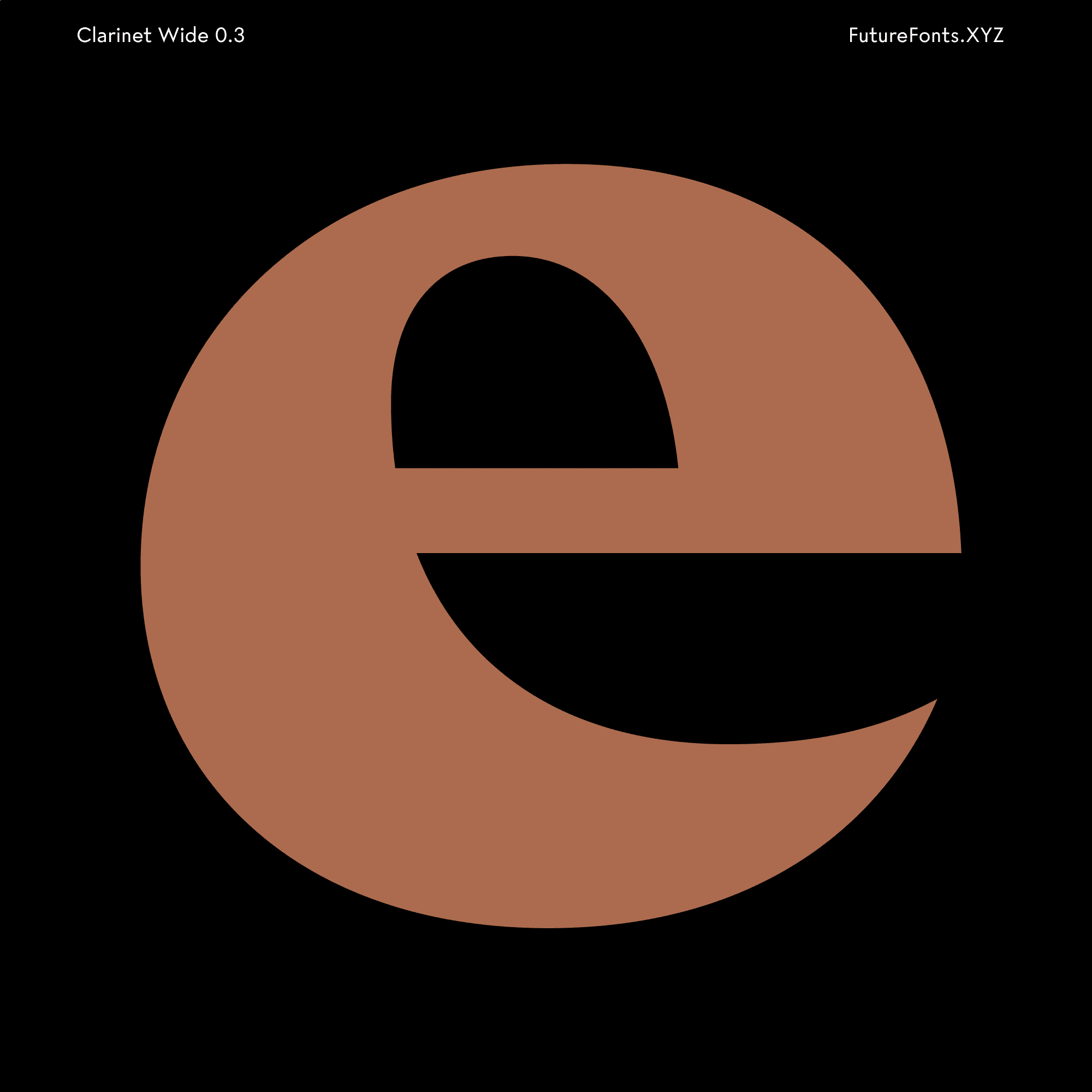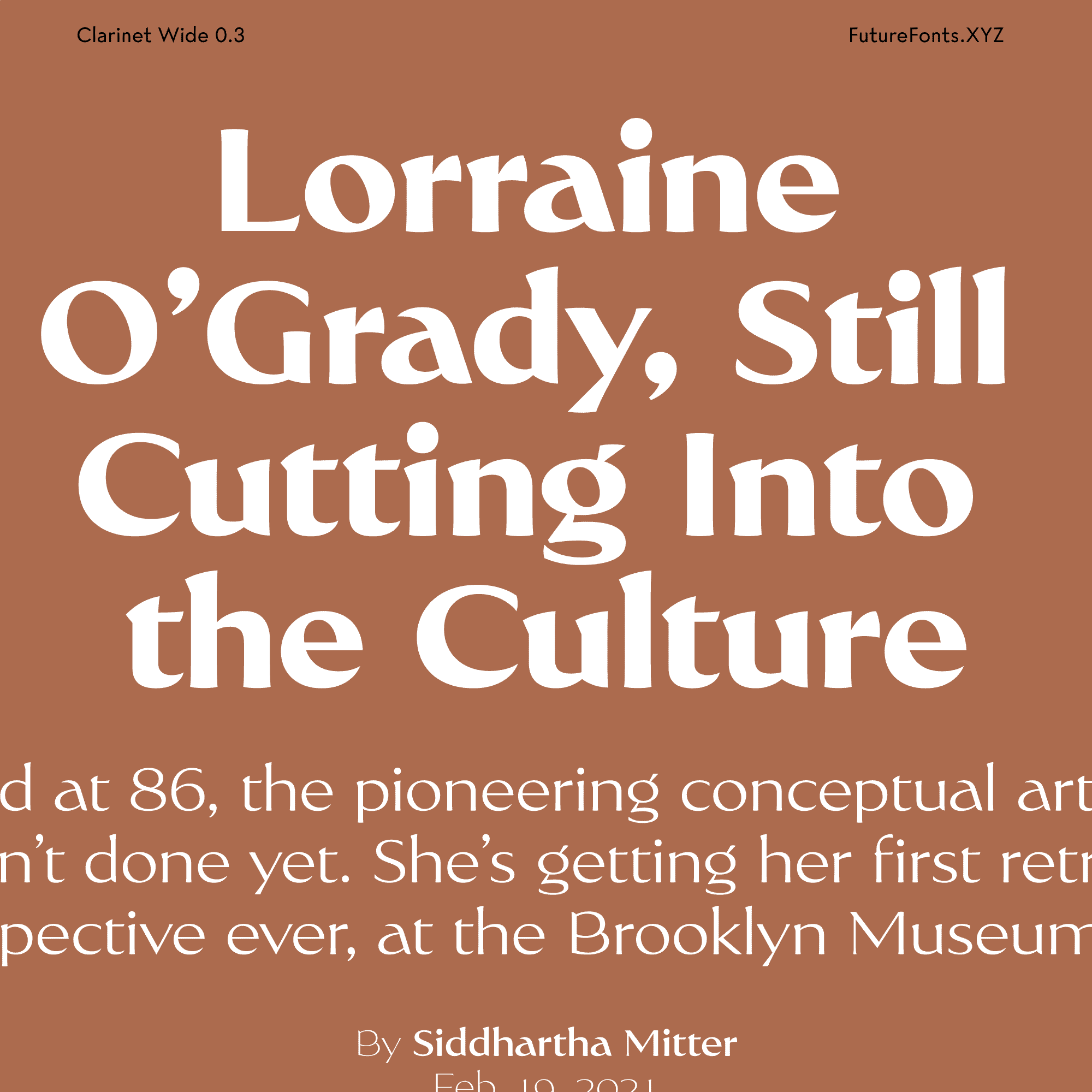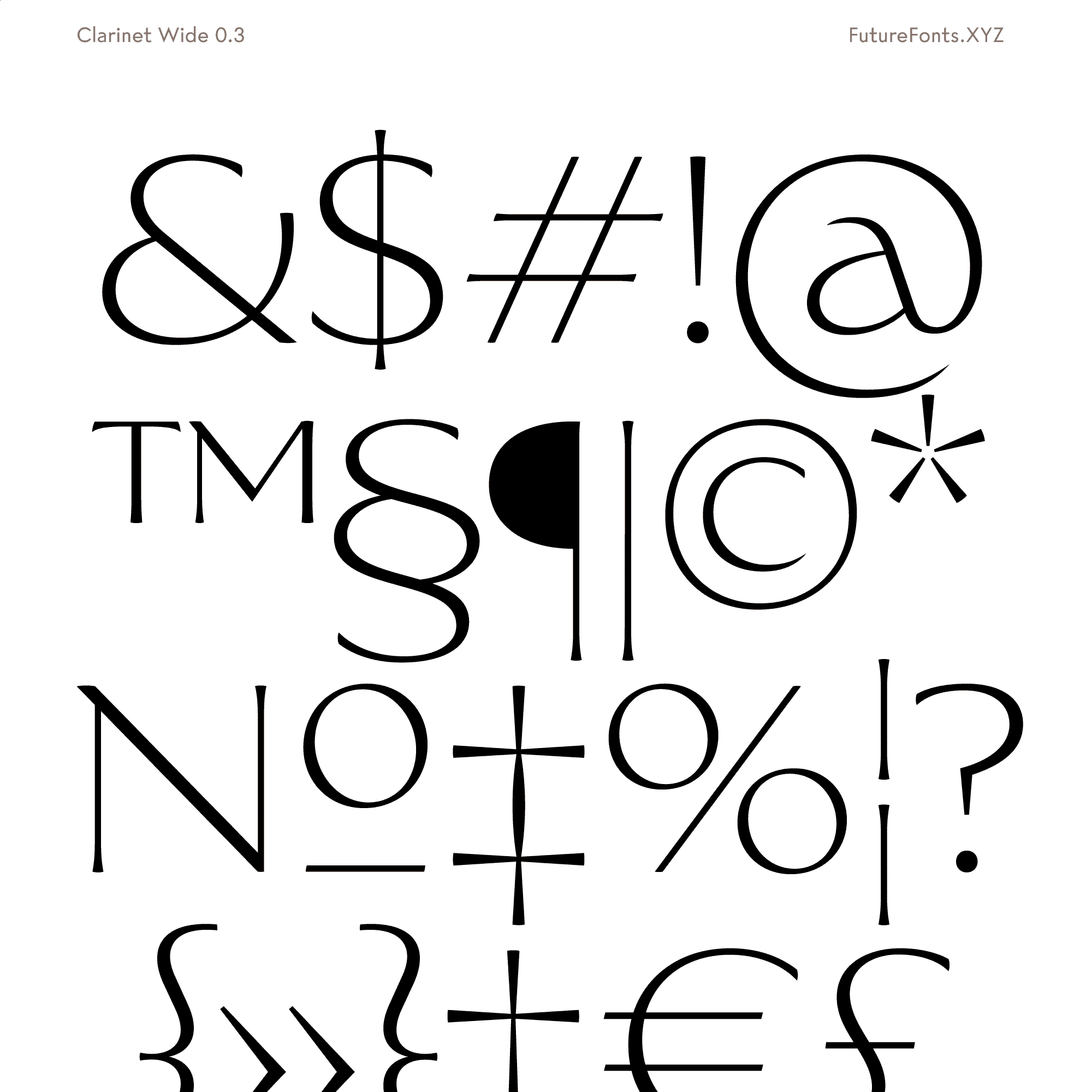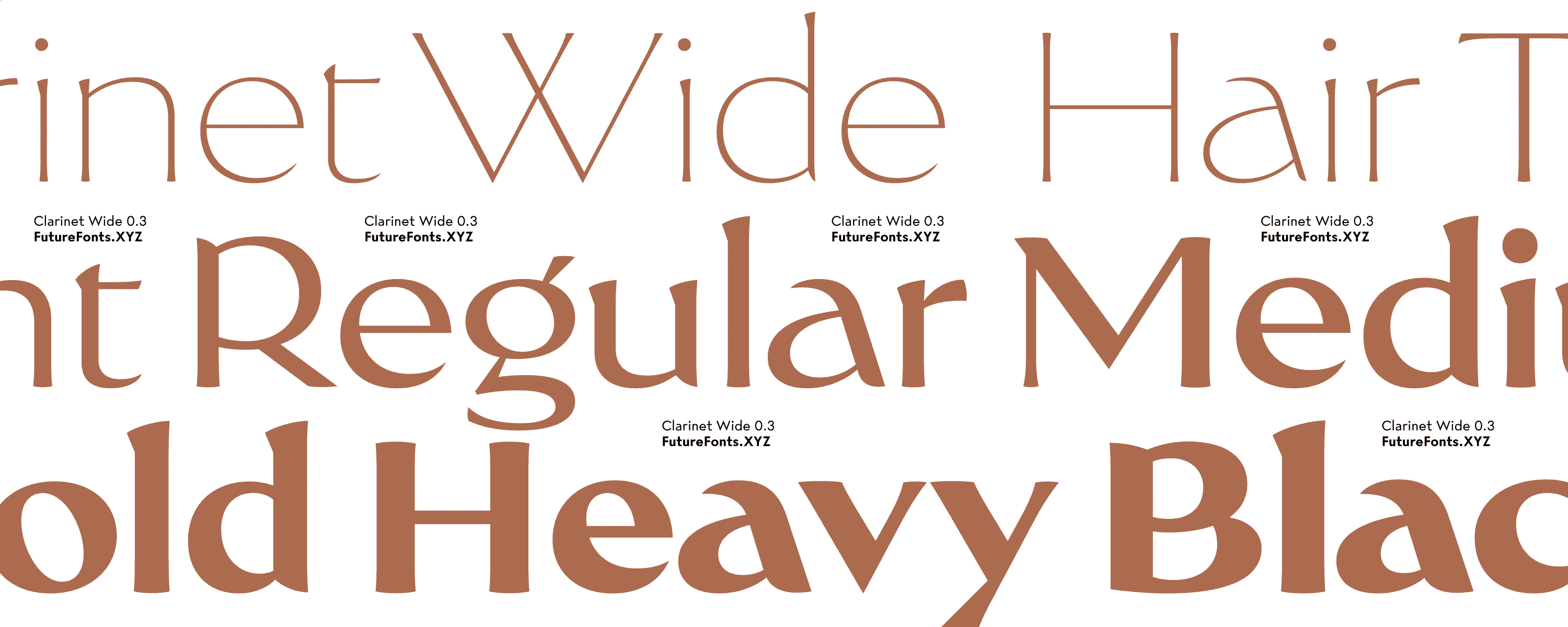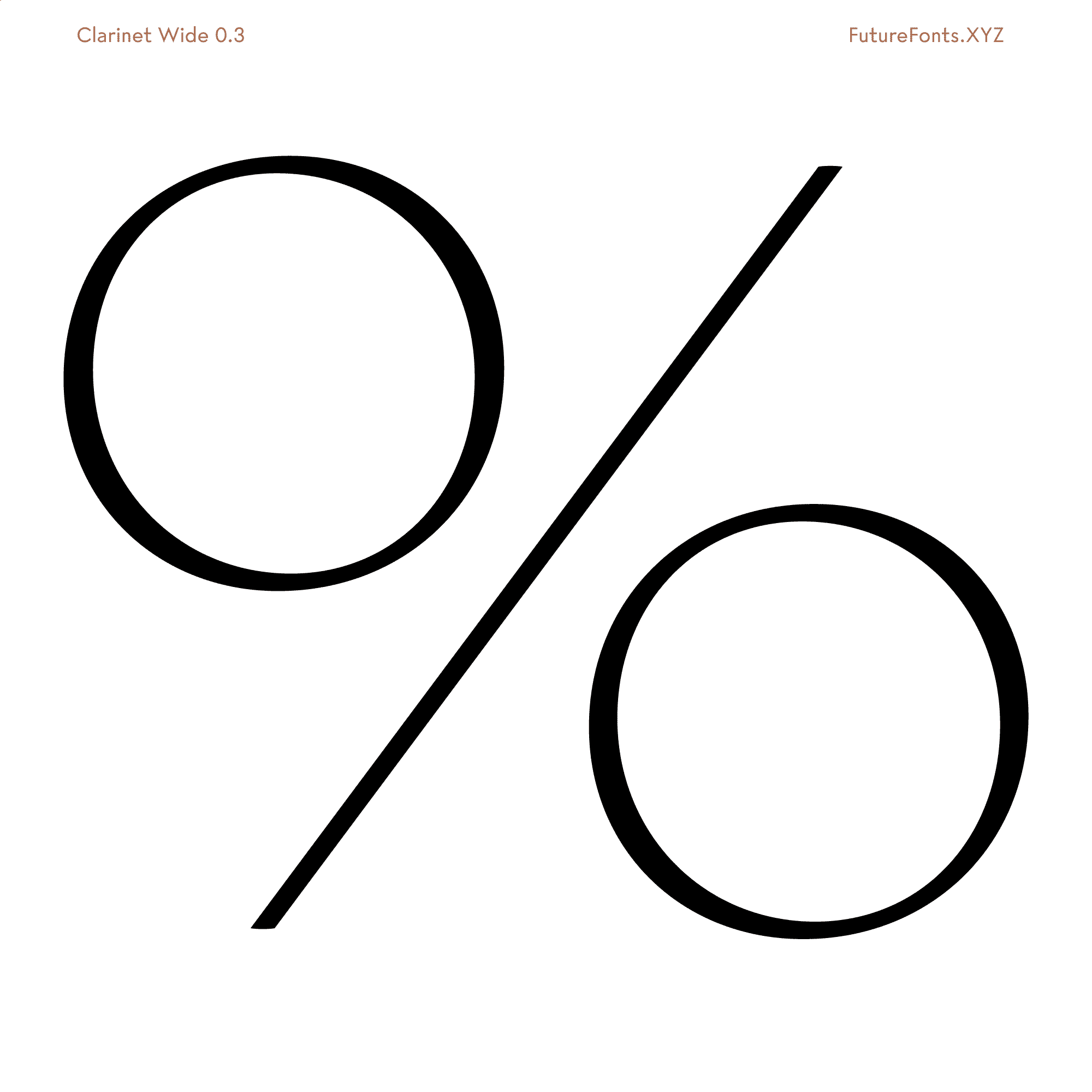
- Clarinet Wide
Štylistická sada 1 ThinageageJednoduché ag
O písme
Všestranné písmo pre použitie v brandingu, obalovom dizajne a dizajne publikácií.
Clarinet Wide je elegantné, sofistikované moderné serifové písmo s rozšírenými zakončeniami ťahov určené pre univerzálne použitie, obsahujúc 8 štýlov v škále od Hair po Black, s vysokým kontrastom, veľkou šírkou a normálnou strednou výškou.
Podporovanými znakovými sadami písma Clarinet Wide sú základná latinka a rozšírená latinka, vďaka čomu môže byť písmo použité vo viac ako 100 jazykoch. S celkovým počtom 396 znakov, základnou sadou sú proporčné zarovnané číslice doplnené o proporčné skákavé číslice a tabulárne zarovnané číslice pre pokročilú numerickú sadzbu. Funkcie ako štylistická sada 1, štandardné ligatúry a ordinály umožňujú ďalšie prispôsobenie a zvyšujú celkovú všestrannosť písma.